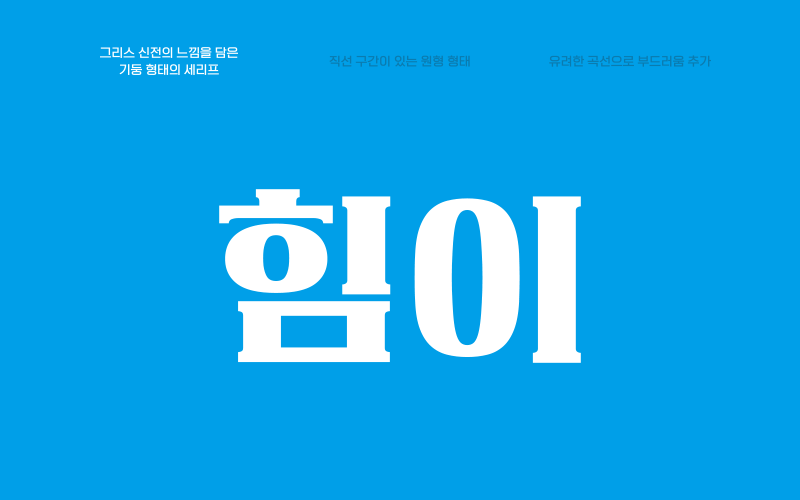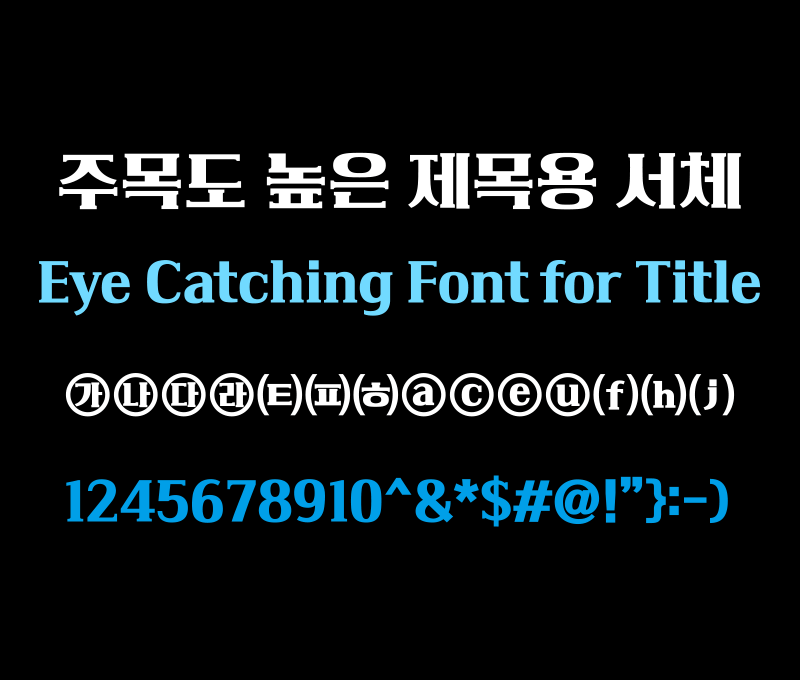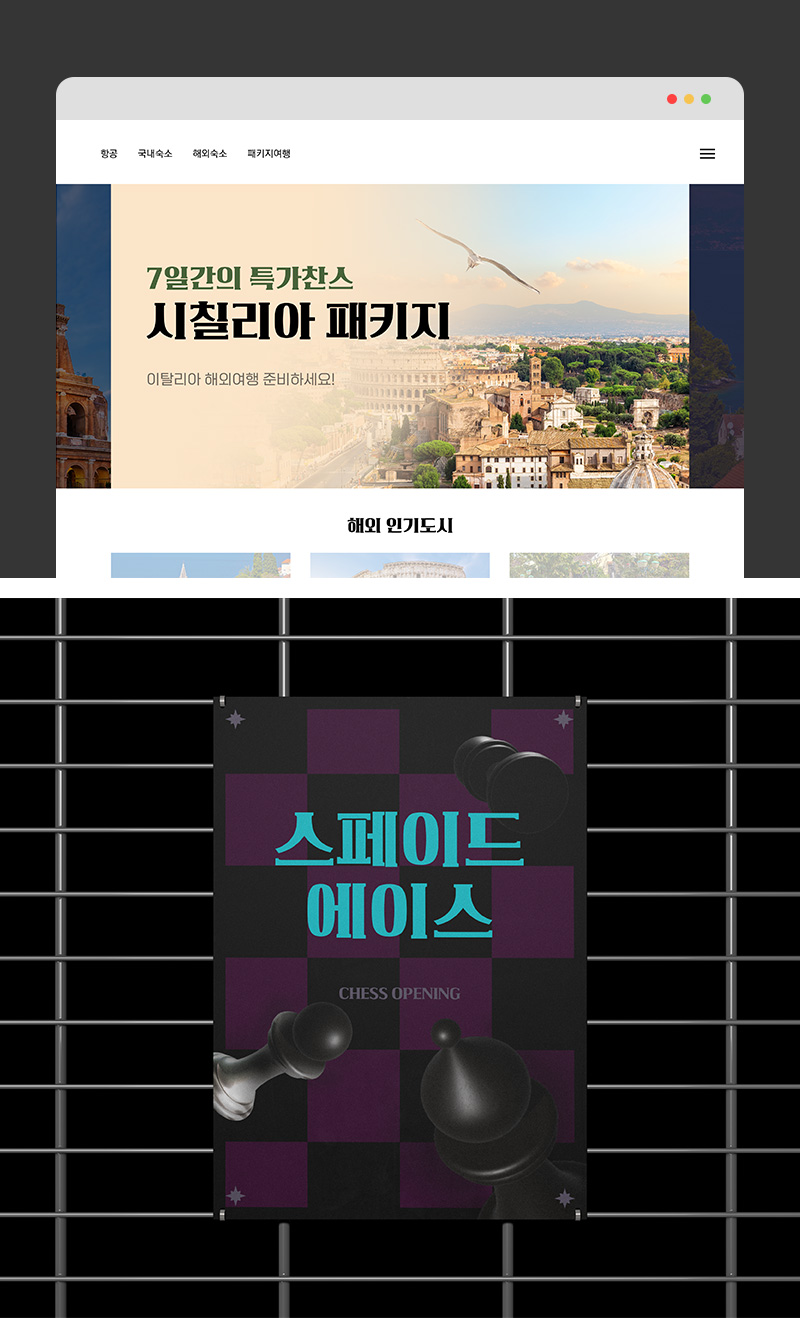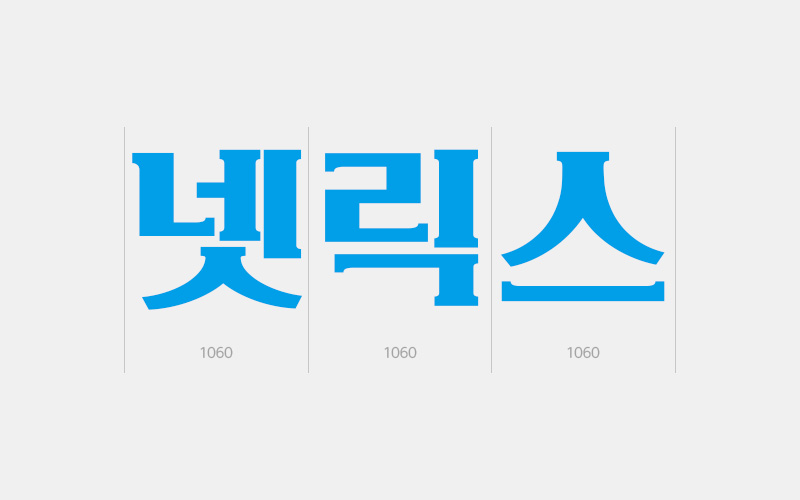
RixAthene
그리스 신전을 모티브로 한 디자인으로 힘 있고 웅장한 인상의 글꼴입니다.
폭이 넓고 꽉 찬 골격의 형태와 장식적인 세리프가 조화롭게 어우러진 특징이 있습니다.
주목도가 높은 서체 스타일로 콘텐츠의 타이틀이나 메인 폰트로 활용하기 좋습니다.
꽃처럼 피어나 별처럼 빛나는 그대에게
넓은 장평의 모듈에 꽉 찬 형태가 특징입니다.
그리스 신전의 느낌을 담은 기둥 형태의 세리프
영문, 약물의 디자인은 한글과 동일한 특징을 가지고 있어 혼용 시 조화롭습니다.